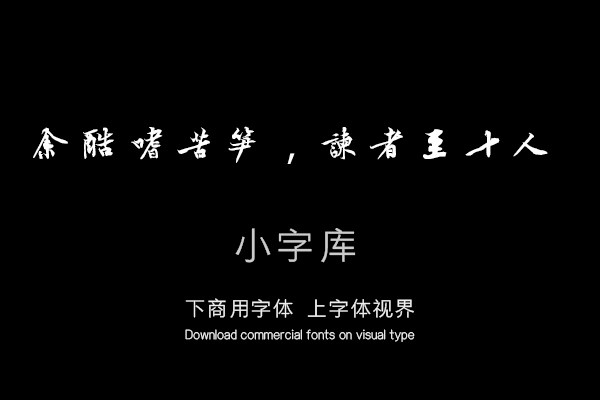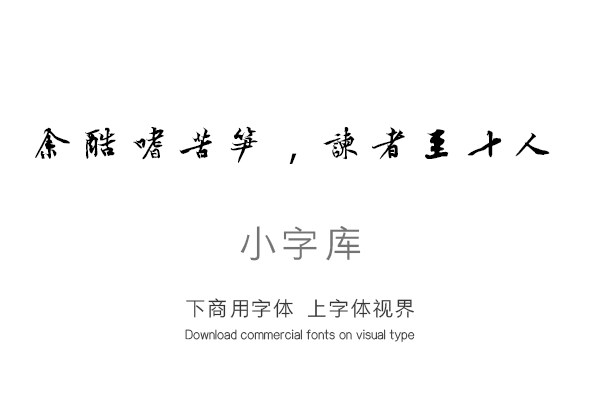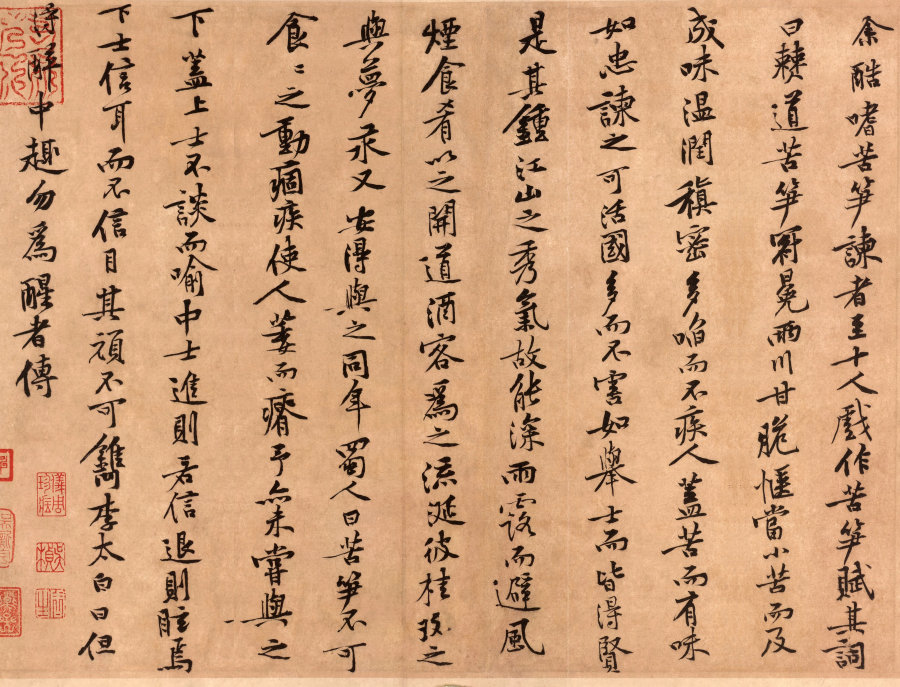
汉标黄庭坚苦笋赋
《汉标黄庭坚苦笋赋》是一款根据北宋黄庭坚《苦笋赋》,经过再次调整制作的小字库,该小字库共收录了该真迹作品中约217个字体。
余酷嗜苦笋,谏者至十人,戏作苦笋赋。其词曰:僰道苦笋,冠冕两川,甘脆惬当,小苦而及成味,温润稹密,多啖而不疾人。盖苦而有味,如忠谏之可活国;多而不害,如举士而皆得贤。是其钟江山之秀气,故能深雨露而避风烟,食肴以之开道,酒客为之流涎,彼桂玫之与梦汞,又安得与之同年。蜀人曰:苦笋不可食,食之动痼疾,使人萎而瘠。予亦未尝与之下。盖上士不谈而喻;中士进则若信,退则眩焉,下士信耳,而不信目,其顽不可镌。李太白曰:“但得醉中趣,勿为醒者传。”